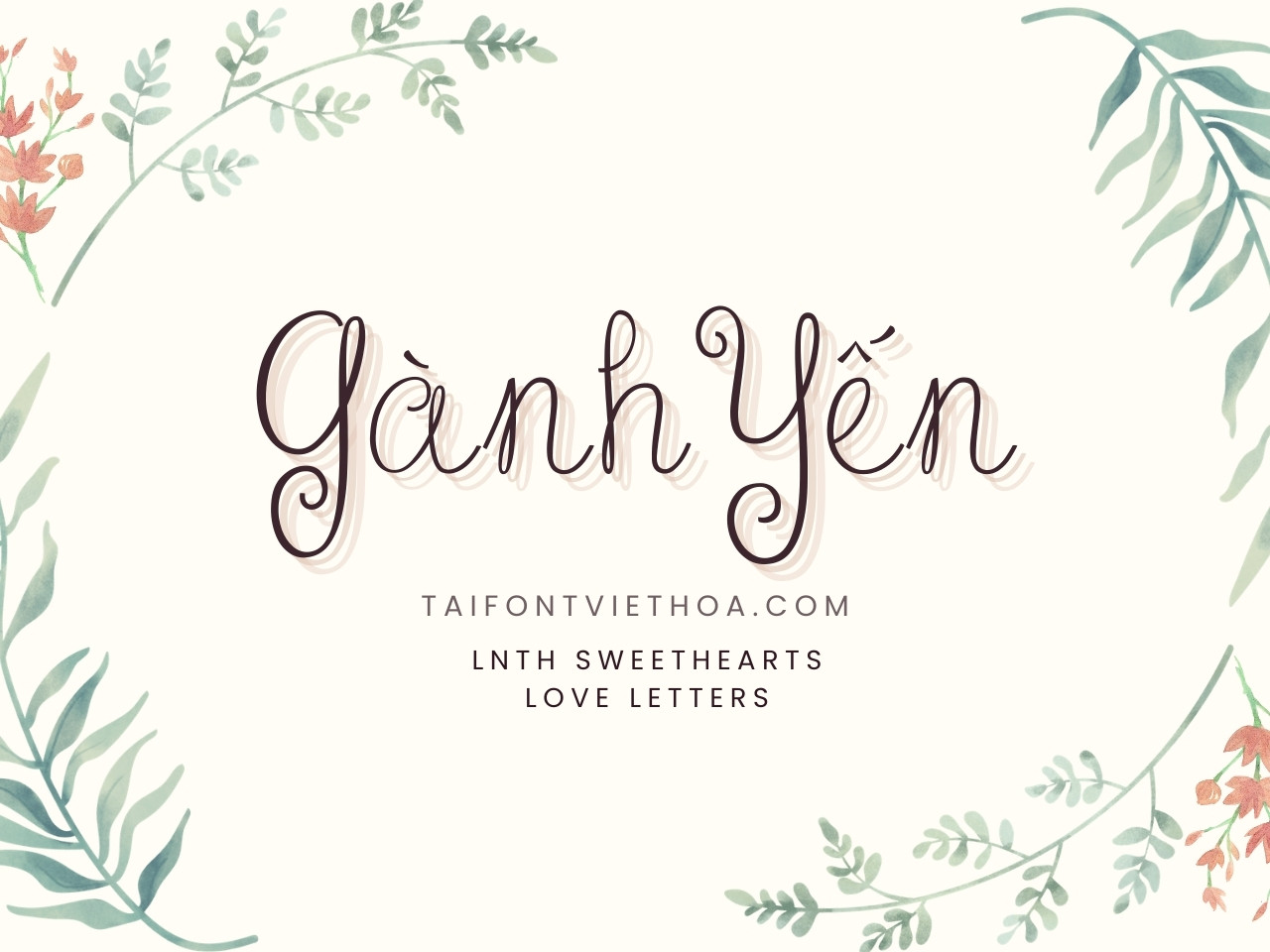
Giới thiệu về font LNTH Sweethearts Love Letters – Tình cảm, nữ tính và lãng mạn
LNTH Sweethearts Love Letters là font chữ Việt hóa từ thiết kế gốc của Emily Spadoni – nhà thiết kế nổi tiếng với các kiểu chữ viết tay mang phong cách nữ tính, nghệ thuật và cảm xúc. Font mang hơi thở của những lá thư tay ngọt ngào, nhẹ nhàng và bay bổng – thể hiện sự quan tâm, gắn kết và lãng mạn. Phiên bản Việt hóa do Tuỳn Pucca thực hiện cẩn thận, hỗ trợ đầy đủ tiếng Việt cùng hơn 60 ngôn ngữ khác.
Font đã được taifontviethoa.com tuyển chọn kỹ lưỡng cho nhóm font phục vụ các thiết kế cá nhân hóa, đặc biệt là các sự kiện tình cảm như Valentine, lễ cưới, sinh nhật hay các dự án nghệ thuật thủ công. Với phong cách duyên dáng và hiệu ứng chữ viết tay tinh tế, LNTH Sweethearts Love Letters đem lại cảm giác gần gũi, chân thành nhưng vẫn rất chuyên nghiệp khi ứng dụng vào thiết kế thực tế.
Đặc điểm thiết kế và ứng dụng nổi bật của font LNTH Sweethearts Love Letters
Font sở hữu kiểu chữ script ngẫu hứng, với các đường nét uốn lượn nhẹ nhàng, cấu trúc linh hoạt và các ligatures sáng tạo – tái hiện hoàn hảo cảm giác viết tay lãng mạn. Nét chữ mảnh, đều và mềm mại giúp dễ dàng truyền tải thông điệp tình cảm, đồng thời phù hợp với nhiều định dạng từ in ấn đến kỹ thuật số.
Font rất phù hợp với các ngành nghề như thiết kế thiệp cưới, mỹ phẩm, thời trang nữ, đồ handmade, ẩm thực, hoặc thương hiệu cá nhân hóa. Các ứng dụng tiêu biểu bao gồm: thiệp Valentine, typography ảnh cưới, thiết kế bìa sổ tay, tiêu đề blog về tình yêu – lifestyle, hoặc các ấn phẩm truyền thông nữ tính và ngọt ngào.